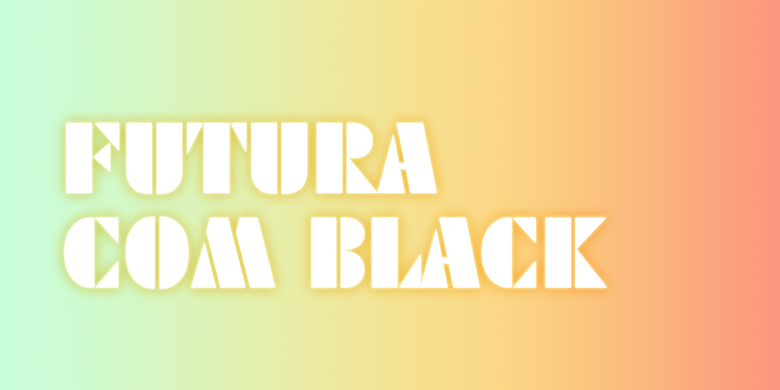
Futura® Com
Futura® Com,这款字体结构工整、笔画清晰,兼顾美观与易读性,适用于标题、正文、海报、包装、LOGO 等多种场景。字形优雅稳定,风格百搭耐看,适配日常排版与创意设计,让文字呈现更舒适、更具质感。Futura® Com一笔一画,皆是细节,以均衡的比例、流畅的线条打造舒适视觉体验,字形端正大气,风格简约现代。无论是商业设计、品牌宣传还是日常排版,都能轻松驾驭,让文字更有格调与力量。Futura® Com字体下载。
字体品牌: Linotype(Monotype) 设计师:Renner,Paul 字体分类:衬线体、无衬线体 字体属性:外文 字符集:Unicode 发布时间: 2018